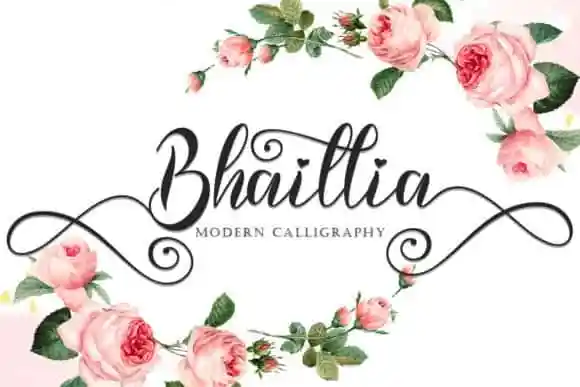
Bhaillia Calligraphy Font é uma fonte de escrita filigranada que traz leveza e beleza à sua arte digital. Suave como os mais belos versos poéticos, esta fonte moderna e elegante irá tornar qualquer projeto gráfico único e singular. Foi criada por yogaletter6 e compartilhada com todos nós no 99designs. Bhaillia Calligraphy Font está perfeitamente equipada para transformar design após design em algo memorável, especialmente quando é usada em elementos que exijam um toque de escrever a mão. Perfeito para cartões de casamento, cartões de agradecimento, citações e cartões de boas-vindas; logos de marcas e até mesmo cartões de negócios. O destaque vão para seus traços fluidos e suaves, sua gama variada de base linha e seu conjunto de grafos incrivelmente belo. Este é um verdadeiro tesouro gráfico que irá deixar qualquer projeto com uma pitada única e atraente. Seja em qualquer aplicação design visual, Bhaillia Calligraphy Font oferece alternativas estonteantes para tornar seus trabalhos ainda mais memoráveis.